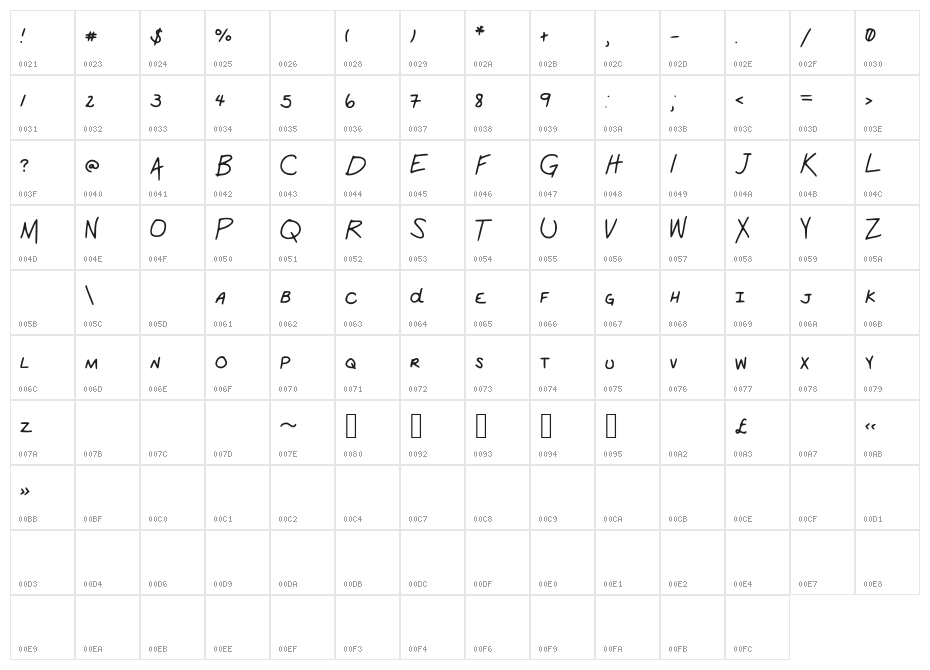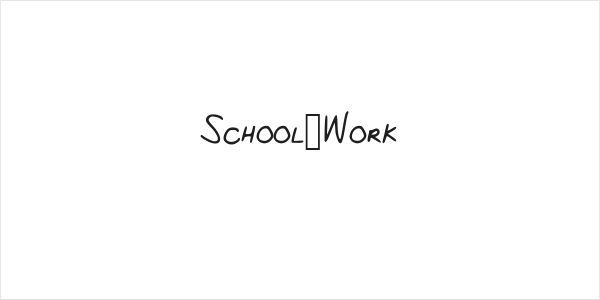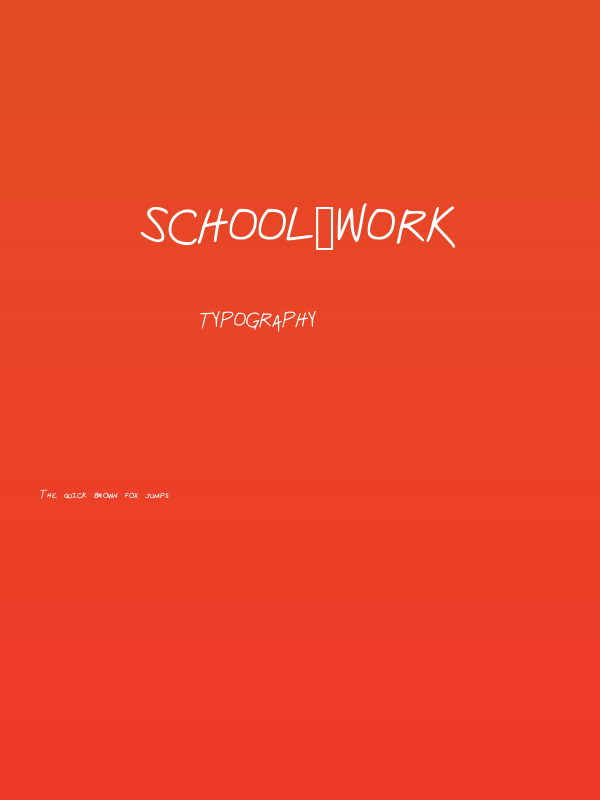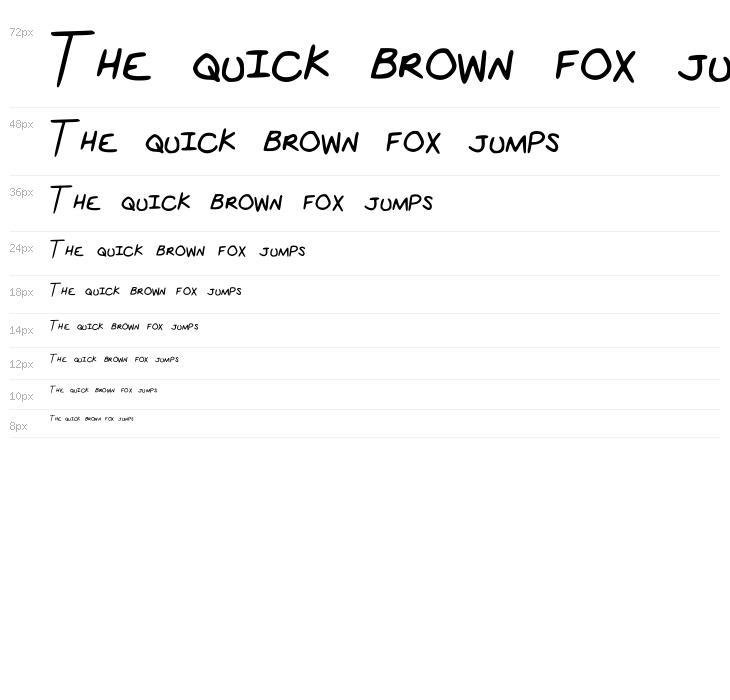
School_Work Font
| 分类 | Handwritten |
| 整体风格 | Casual |
| 使用场景 | Headlines, Informal text, Educational materials |
| 推荐项目 | Ideal for children's books, greeting cards, casual invitations, and educational materials. |